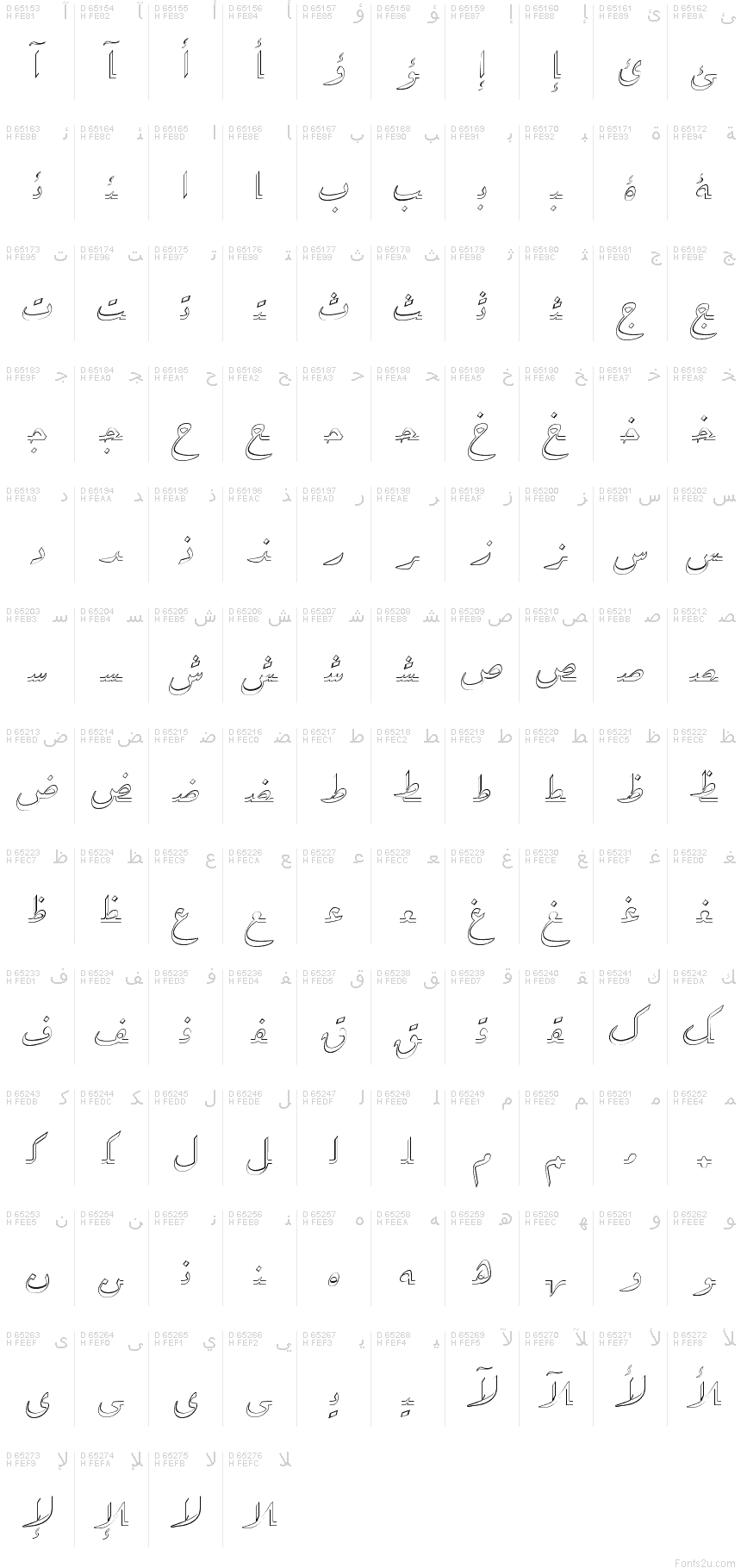
Sepideh Outline autorstwa Borna Rayaneh to darmowy arabski font typu outline o płynnym, kaligraficznym charakterze. Litery przypominają raczej zwiewne wstęgi niż pełne kształty, łącząc gładkie krzywizny z ostrymi złączeniami, co nadaje krojowi formę uroczystą, lekką i nieco ceremonialną.
To naturalny wybór na okładki książek, plakaty kulturalne, opakowania, napisy tytułowe i krótkie linie brandingowe, gdzie otwarty kontur pozwala na zdobienia bez efektu ciężkości. Jako darmowy font, doskonale sprawdzi się w krótkich nagłówkach, monogramach i napisach, które zyskają na pełnym wdzięku arabskim rytmie oraz sposobie, w jaki obrysowane znaki dają stronie oddech.